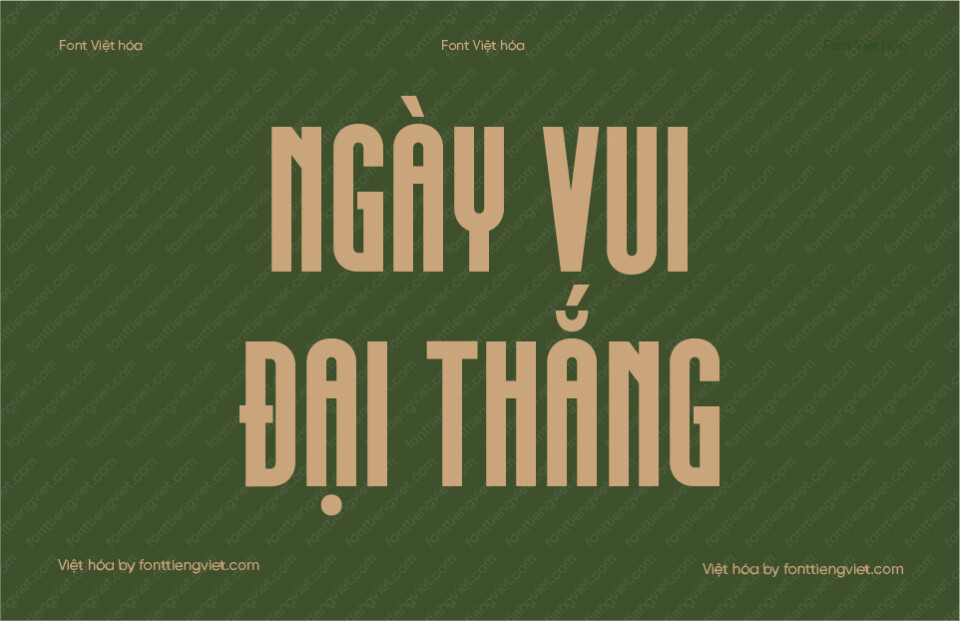
Font Việt hóa 1FTV VIP Normiyola – Font chữ không cân mạnh mẽ, đậm chất cổ điển cho thiết kế lịch sử và quảng cáo in ấn
Giới thiệu về Font Việt hóa 1FTV VIP Normiyola – Font chữ không cân mạnh mẽ, đậm chất cổ điển cho thiết kế lịch sử và quảng cáo in ấn
Trong thế giới đồ họa hiện đại, việc tìm kiếm một bộ Font Chữ mang đậm hơi thở thời gian nhưng vẫn giữ được sự chắc chắn là điều không dễ dàng. Font Việt hóa 1FTV VIP Normiyola – Font chữ không cân mạnh mẽ, đậm chất cổ điển cho thiết kế lịch sử và quảng cáo in ấn chính là giải pháp hoàn hảo cho những nhà thiết kế đang theo đuổi phong cách retro. Với cấu trúc các đường nét dày dặn và bố cục không cân đối một cách nghệ thuật, bộ font này tạo ra sự khác biệt lớn so với các phông chữ truyền thống, giúp tác phẩm trở nên nổi bật và có chiều sâu văn hóa hơn.
Đặc điểm nổi bật của bộ font chữ không cân Normiyola
Bộ font này gây ấn tượng bởi những nét vẽ thô mộc nhưng đầy tinh tế, gợi nhớ đến các bảng hiệu quảng cáo từ thế kỷ trước. Tính chất “không cân” mang lại vẻ đẹp tự nhiên, giúp người xem cảm nhận được sức mạnh và sự kiên định trong từng con chữ. Đây là lựa chọn tối ưu cho những tiêu đề sách lịch sử, poster triển lãm hoặc các ấn phẩm truyền thông đòi hỏi sự trang trọng và uy nghiêm.
Ứng dụng Font Việt hóa 1FTV VIP Normiyola vào thực tiễn thiết kế
Nhờ đặc tính mạnh mẽ, font chữ này cực kỳ hiệu quả khi áp dụng vào lĩnh vực quảng cáo in ấn. Các chuyên gia thường sử dụng nó cho bao bì sản phẩm thủ công, bìa tạp chí nghệ thuật hoặc các chiến dịch truyền thông mang tính hoài cổ. Khả năng hiển thị sắc nét của nó đảm bảo thông điệp luôn rõ ràng dù in trên nhiều chất liệu khác nhau.
Lợi ích khi sử dụng font Việt hóa chuẩn
Việc sử dụng phiên bản Việt hóa giúp các bạn học sinh và nhà thiết kế tại Việt Nam dễ dàng thể hiện nội dung tiếng Việt mà không lo lỗi dấu. Điều này không chỉ đảm bảo tính thẩm mỹ mà còn giúp tiết kiệm thời gian chỉnh sửa kỹ thuật, tập trung hoàn toàn vào sự sáng tạo cho các dự án học tập và công việc chuyên môn.
Kết luận về giá trị của Font Việt hóa 1FTV VIP Normiyola
Tóm lại, bộ Font Việt hóa 1FTV VIP Normiyola – Font chữ không cân mạnh mẽ, đậm chất cổ điển cho thiết kế lịch sử và quảng cáo in ấn là một công cụ đắc lực cho bất kỳ ai muốn truyền tải sự mạnh mẽ và tinh thần lịch sử vào tác phẩm của mình. Nếu bạn đang tìm kiếm sự độc đáo cho bộ sưu tập cá nhân, hãy trải nghiệm ngay mẫu Font Miễn Phí, Font Việt Hóa, Font Việt hóa 1FTV VIP Normiyola – Font chữ không cân mạnh mẽ, đậm chất cổ điển cho thiết kế lịch sử và quảng cáo in ấn để nâng tầm chất lượng đồ họa của mình ngay hôm nay.